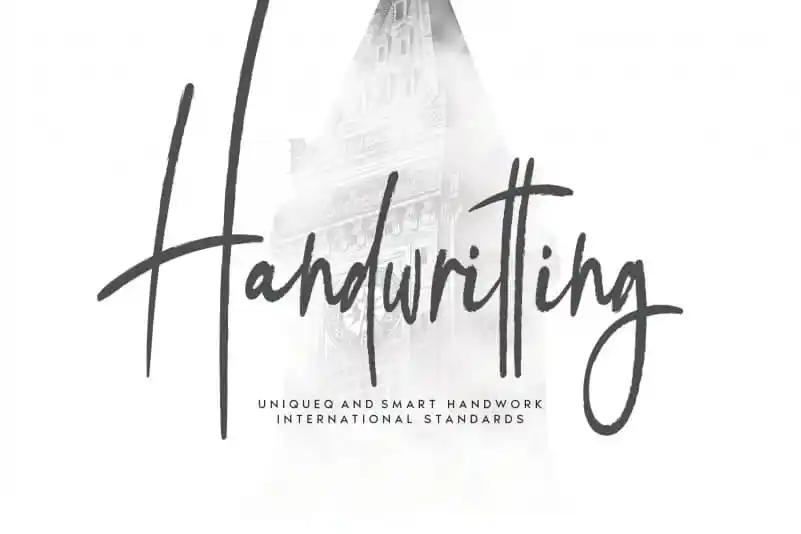
Aqui está uma descrição em português do Brasil para a página de download da fonte ‘Handwritting Script Font’, seguindo as instruções fornecidas: É hora de personalizar sua marca ou projeto com um ar sofisticado e autêntico, usando a Handwriting Script Font. Especificamente projetada para designers e criativos como você, esta fonte traz uma experiência única e única, proporcionando um toque especial em qualquer layout. Suas ideias brilham mais quando são escritas de forma natural e autêntica, não é? É exatamente isso que a Handwriting Script Font oferece. Ela captura o espírito da escrita à mão livre, resultando em uma aparência fluida e elegante. Sua versão criativa e personalizada irá tornar qualquer projeto mais único e singular. Com a Handwriting Script Font, você pode adicionar um toque autêntico aos seus materiais de design sem gastar tempo transformando letras manuscritas em digitais. Estamos certos de que sua comunicação será ainda mais forte quando for personalizada dessa maneira. A fonte vem com uma ampla gama de opções, incluindo várias tipografias e tamanhos, para garantir a melhor experiência de uso e um design fluido em qualquer projeto. Seja para o seu blog, livro impresso ou marca digital – esta fonte é certamente sua escolha ideal.